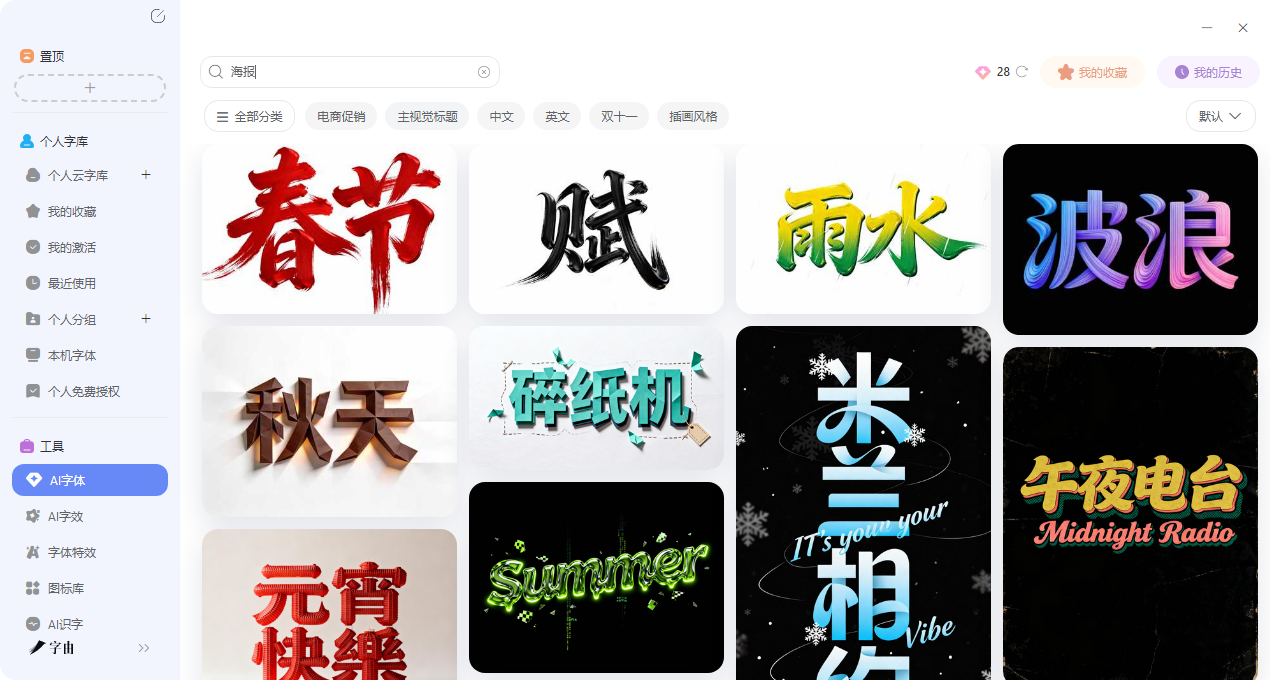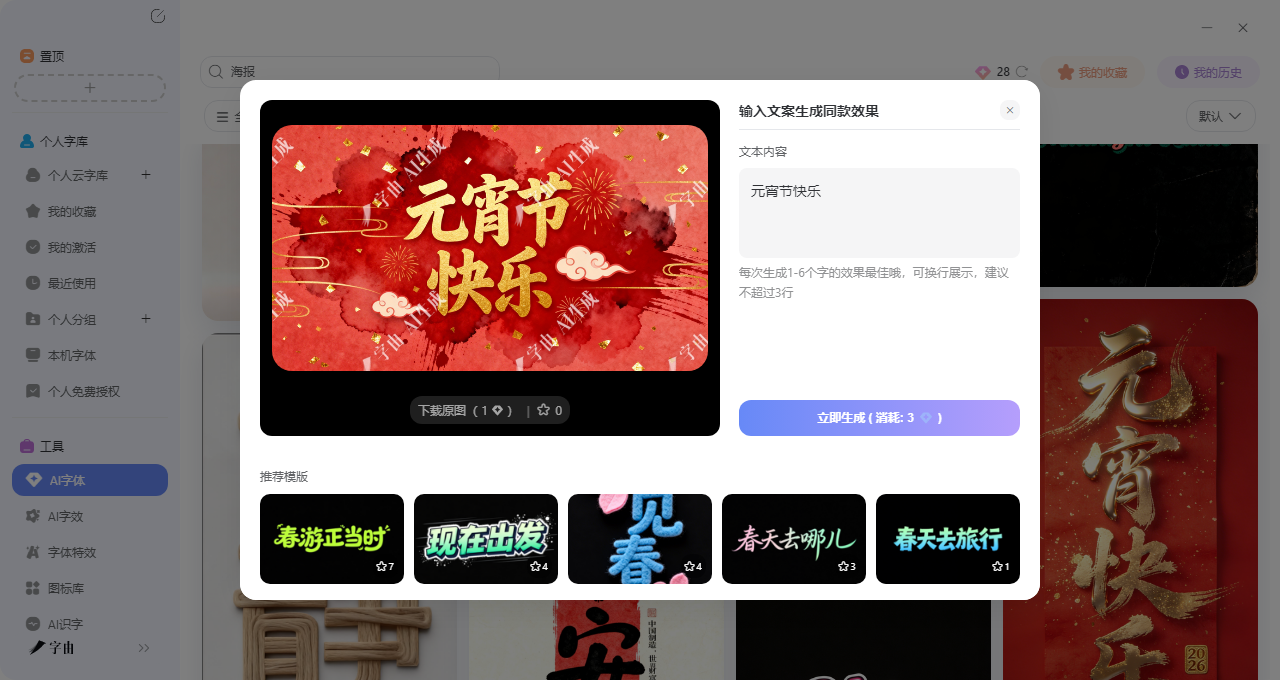
海报标题不吸睛?试试这几个字体生成工具,效果惊艳
你有没有过这种经历:辛辛苦苦做完一张海报,构图、配色、排版都花了心思,可放到屏幕上就是觉得哪里不对。反复看才发现,是标题字出了问题——太普通了,压不住画面,也抓不住眼球。一张海报的灵魂往往就在那几个标题字上。选对了,整张画面都活了;选错了,再好的设计也救不回来。以前想做个出彩的海报标题,要么在PS里调图层样式调半天,要么到处翻字体网站碰运气。现在不一样了,海报标题字体生成工具让你输入文字就能一键搞定。今天我就筛选了 4 个亲测好用的工具,希望可以帮到你。
如果你细心的话就会发现,那些有高级感、受大众喜欢的海报,往往标题不是那种基础的字体,而是带着特殊效果的艺术字——要么是霓虹闪烁,要么是金属质感,要么是水彩晕染。今天我会给大家介绍怎么在字由里搜索并免费使用AI 字体来制作漂亮的海报:
第一步:进入AI字体页面后,在搜索框里输入“海报标题”,系统会自动筛选出所有适合做海报标题的模板。你也可以试试“主视觉标题”“Banner设计”这些词。
第二步:搜索结果会展示各种风格的预览图,每个模板都有独特的设计:
- 复古霓虹类:“午夜电台”这种,适合音乐、夜生活主题
- 文艺手写类:“秋天”这种,适合季节限定、生活方式类
- 节日喜庆类:“元宵节快乐”这种,适合节日促销、活动预告
- 破坏冲击类:“碎纸机”这种,适合摇滚、街头文化
- 夏日活力类:“Surmmer”这种,适合派对、度假主题
- 简约高级类:“米兰相约”这种,适合时尚、艺术设计
每个模板都有预览图,你可以先看效果再决定,点进去还能看到更多细节。选一个和你的海报风格搭的,如果拿不准,可以多试几个。
第三步:点击选中的模板,进入编辑页面。在输入框里填你想生成的标题文字,比如“夏日音乐节”“秋季限定”“新年狂欢”。注意:最好和模板的字数保持一致,模板是四个字,你就填四个字;模板是两个字,你就填两个字。
第四步:确认文案后,点“立即生成”,等20-30秒左右就能拿到图。生成后可以预览效果,不满意就换其他模板再试,或者微调文案重新生成。每天有免费算力点,日常试用完全够用!
如果你还是不知道要怎么选择,我在这里可以给你做几个推荐:
- “午夜电台”:这个模板是复古霓虹风格,带着一点深夜电台的慵懒和神秘感。适合做音乐节海报、Livehouse演出海报、或者任何需要夜晚氛围的设计。深色背景配上霓虹色的字,氛围感直接拉满。
- “秋天”:这个模板是温柔的手写风格,笔触带着一点水彩感。适合做季节限定活动、咖啡店新品、文艺市集的海报。棕黄色调配上落叶纹理,秋天的那种慵懒和温柔一下子就出来了。
- “元宵节快乐”:这个模板是喜庆的节日风格,字体圆润可爱,带着灯笼和烟花的装饰元素。适合做节日促销、活动预告、或者给粉丝的节日祝福海报。大红底色配上金色描边,年味儿十足。
其实字由AI 字体模板要比你想象得丰富得多,它不仅仅包括海报标题这个分类,你还可以在“节日风”“国潮风”“电商促销”里找一些有趣的模板。
2、Best Poster Fonts – Google Fonts
Best Poster Fonts 是一个专门推荐海报字体的网站,它从Google Fonts里精选了14款最适合做海报标题的字体,每一款都经过严格筛选,确保可读性、字重多样性和搭配灵活性。如果你因为主页的推荐而想要一款字体,它也提供了下载的跳转链接,其中我比较喜欢的字体有:
- Montserrat:3种字重,无衬线体。灵感来自布宜诺斯艾利斯历史街区的招牌,适合城市、几何、大写友好、响亮、海报等场景。这款字体可以说是海报设计的万金油,现代感强,几乎不会出错。
每款字体都有详细的预览,可以输入自己的文字看效果,还提供了“VISUALIZE PAIRING”功能,方便你搭配其他字体使用。
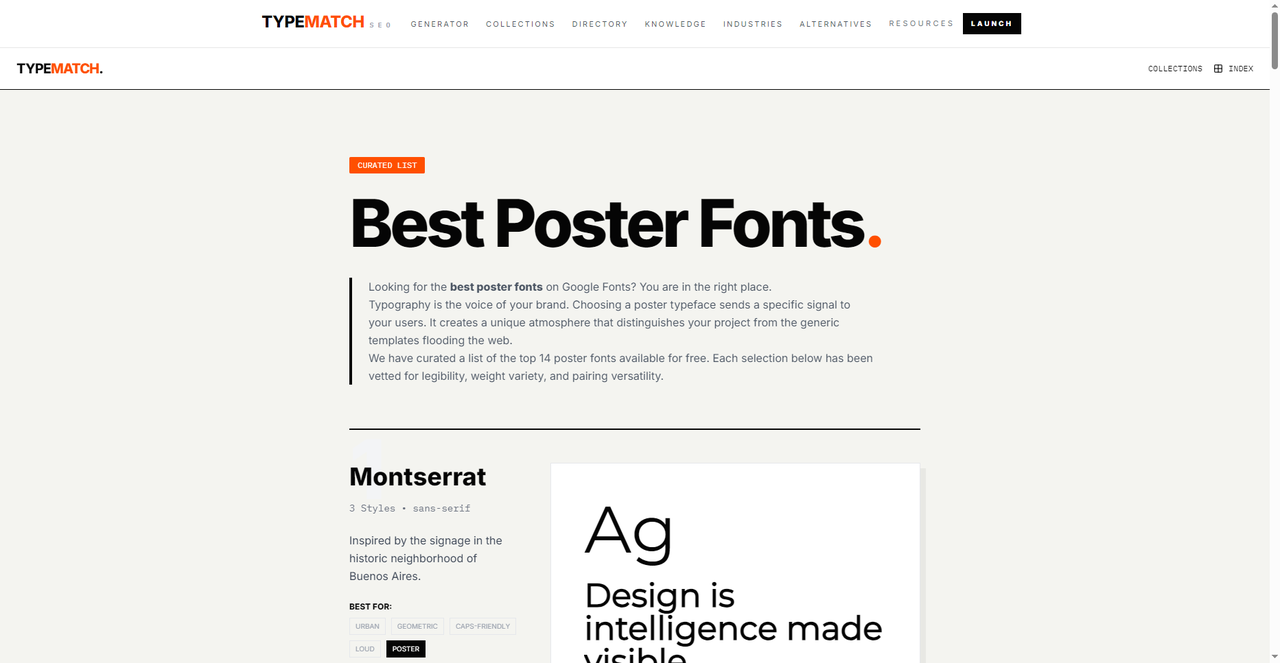
3、FontGet
FontGet 是一个分类非常细致的免费字体网站。从上面的分类你就知道了,
包括“poster”分类,而且还有按风格细分的选项:
- basic:sans serif、serif、italic等基础字体
- party:wedding、tattoo、birthday、halloween、christmas等派对节日字体
- old school:retro、vintage、typewriter等复古字体
截图里还展示了几个热门海报字体的预览,比如“STRANGER THINGS”(怪奇物语同款字体)、“JUJUSU KAISEN”(咒术回战风格)、“QETOD”“KODYZ”等。这些字体本身就带着很强的IP感和风格标签。
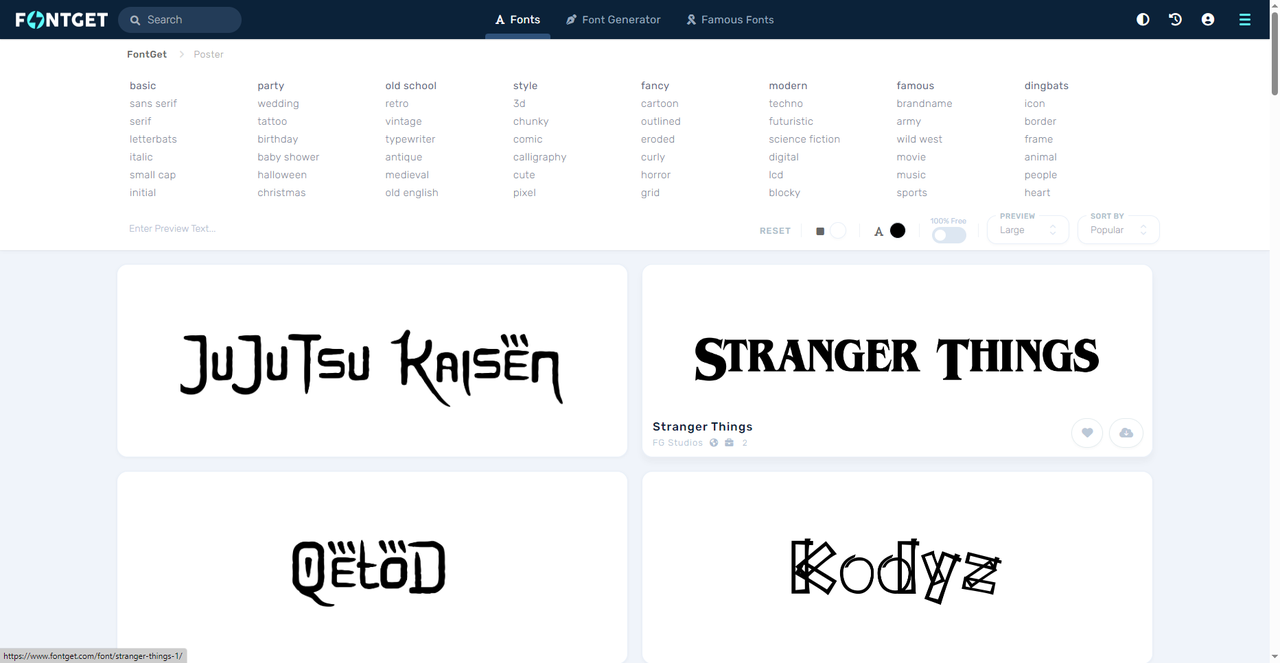
4、1001 Free Fonts
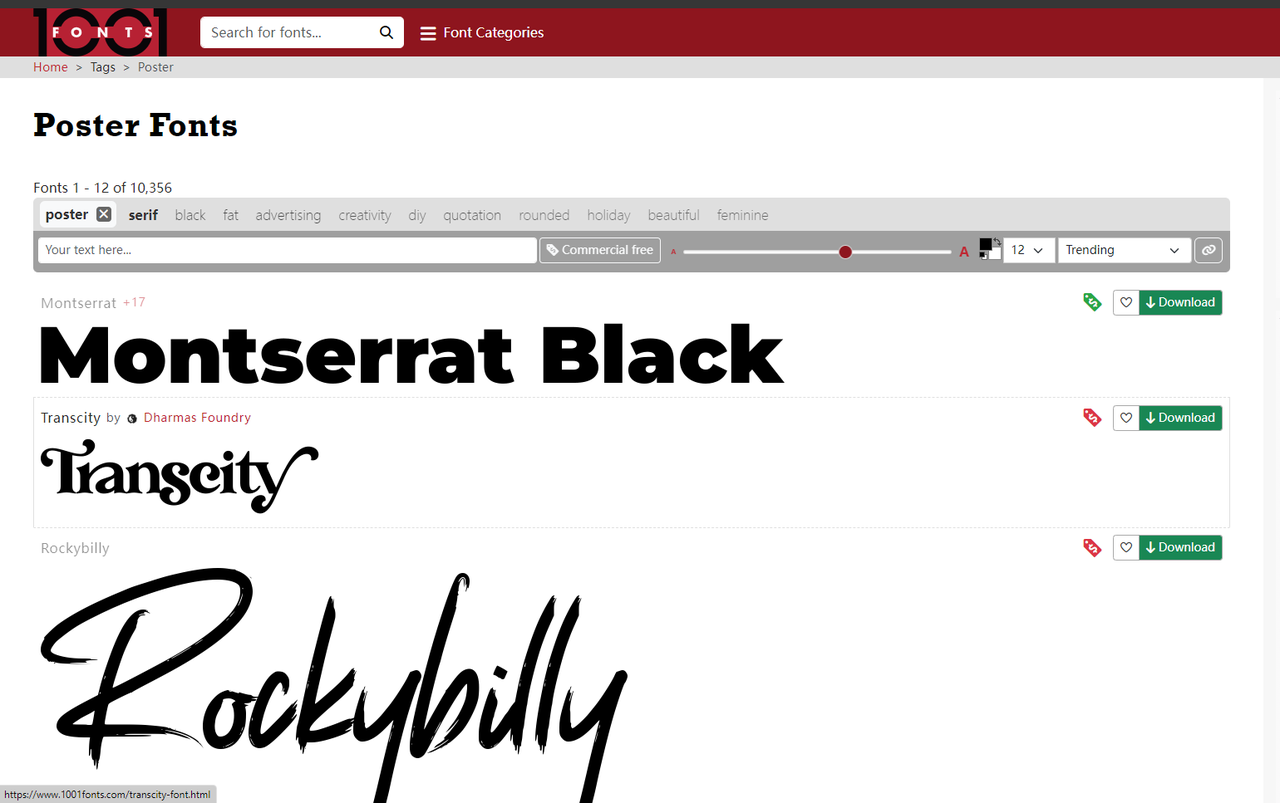
一张好的海报,灵魂一定是上面的标题,以前设计师们可能会苦恼于如何设计出一个惊艳的字体,甚至也会绞尽脑汁去思考什么样的字体会适合海报的整体调性,但是现在有了这些海报标题字体生成工具,一切都非常简单了。在这几个网站里,对我来说最好用的是字由,别的网站虽然也很好但是字由的AI 字体实在是帮我省去了很多麻烦,如果你也想让海报一秒吸睛,不妨去试试字由。